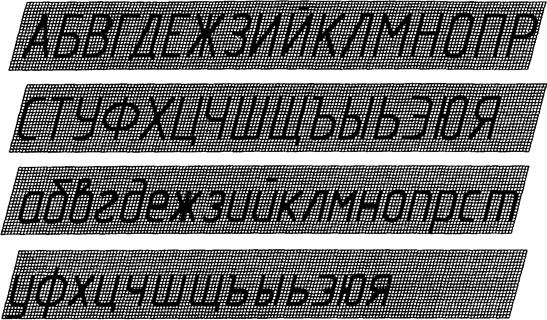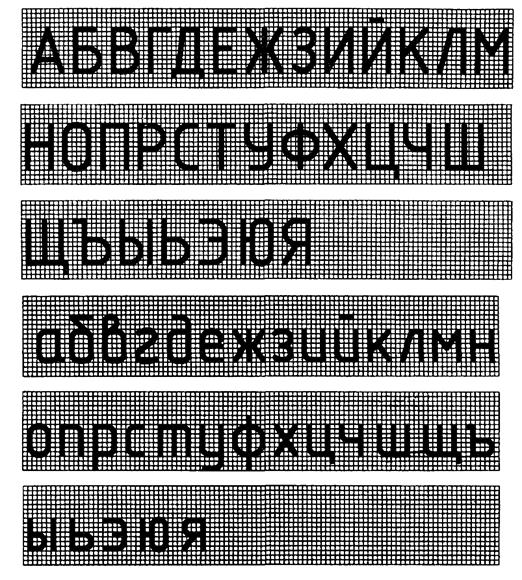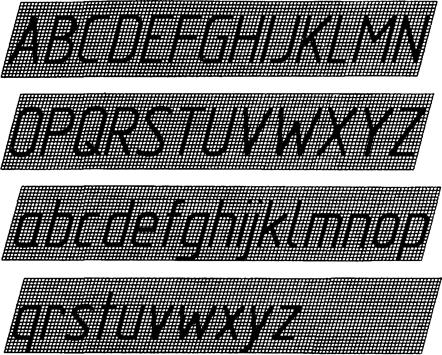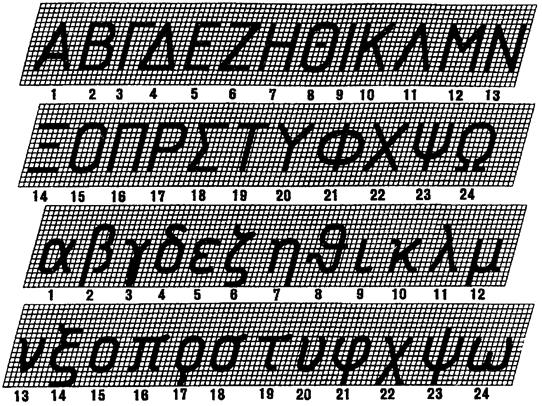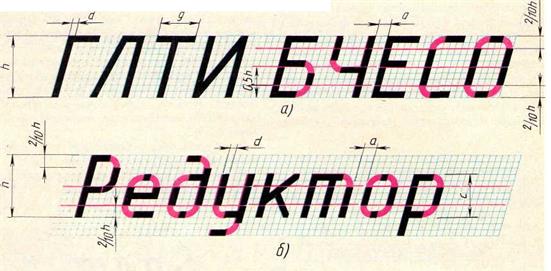
Шрифты чертежные
Линии.
При выполнении любого чертежа основными элементами являются линии. ГОСТ2.303—68 устанавливает начертания и основные назначения линий на чертежах всех отраслей промышленности и строительства.Наименование, начертание, толщина линий по отношению к толщине основной линии и основные назначения линий должны соответствовать указанным в табл. 1.
Таблица 1
Наименование Начертание Толщина линии по отношению к толщине основной линии Основное назначение
1.Сплошная толстая основная s Линии видимого контура Линии перехода видимые Линии контура сечения (вынесенного и входящего в состав разреза)
2.Сплошная тонкая От до Линии контура наложенного сечения Линии размерные и выносные Линии штриховки Линии-выноски Полки линий-выносок и подчеркивание надписей Линии для изображения пограничных деталей («обстановка») Линии ограничения выносных элементов на видах, разрезах и сечениях Линии перехода воображаемые Следы плоскостей, линии построения характерных точек при специальных построениях
3.Сплошная волнистая   Линии обрыва Линии разграничения вида и разреза
4.Штриховая   Линии невидимого контура Линии перехода невидимые
5.Штрихпунктир-ная тонкая От до Линии осевые и центровые Линии сечений, являющиеся осями симметрии для наложенных или вынесенных сечений
6.Штрихпунктир-ная утолщенная От до Линии, обозначающие поверхности, подлежащие термообработке или покрытию Линии для изображения элементов, расположенных перед секущей плоскостью («наложенная проекция»)
7.Разомкнутая От s до Линии сечений
8.Сплошная тонкая с изломами От до Длинные линии обрыва
9.Штрихпунктир-ная с двумя точками тонкая От до Линии сгиба на развертках. Линии для изображения частей изделий в крайних или промежуточных положениях Линии для изображения развертки, совмещенной с видом
Толщина сплошной основной линии s должна быть в пределах от 0,5 до 1,4 мм в зависимости от величины и сложности изображения, а также от формата чертежа. Толщина линий одного и того же типа должна быть одинакова для всех изображений на данном чертеже, вычерчиваемых в одинаковом масштабе. Длину штрихов в штриховых и штрихпунктирных линиях следует выбирать в зависимости от величины изображения. Для штриховой линии длина штрихов равна примерно от 2 до 8 мм (для формата А3 – 5мм), рассто­яние между штрихами 1...2 мм. Для штрихпунктирной линии длина штрихов должна быть равна примерно от 5 до 30 мм (для формата А3 – 15мм), расстояние между штрихами рекомендуется брать 2...3 мм. Штрихи в линии и промежутки между штрихами в линии должны быть приблизительно одинаковой длины. Штрихпунктирные линии должны пересекаться и заканчиваться штрихами.
Штрихпунктирные линии, применяемые в качестве центровых, следует заменять сплошными тонкими линиями, если диаметр окружности или размеры других геометрических фигур в изображении менее 12 мм (рис. 1.3).
Рис. 1.3
Длина штрихов разомкнутой линииберется 8...20 мм в зависимости от величины изображения (для формата А3 – 10мм). Для сложных разрезов и сечений допускается концы разомкнутой линии соединить штрихпунктирной тонкой линией.
Примеры применения линий показаны на рис. 1.4. Номера позиций соответствуют номерам пунктов табл. 1.
Рис. 1.4
Чертежи и прочие конструкторские документы всех отраслей промышленности и строительства содержат необходимые надписи: название изделий, размеры, данные о материале, обработке деталей, специфика­ции и другие надписи.Если надписи на чертежах сделаны небрежно, то при изготовлении деталей по таким чертежам возможны ошибки.ГОСТ 2.304—81 (устанавливает чертежные шрифты, наносимые на чертежи и другие технические документы всех отраслей промышленности и строительства.
Размер шрифта h - величина, определенная высотой прописных букв в миллиметрах.
Высота прописных букв h измеряется перпендикулярно к основанию строки.
Высота строчных букв с определяется из отношения их высоты (без отростков k) к размеру шрифта h, например, с = 7/10 h (рис. 1.5 и 1.6).
Ширина буквы g - ширина буквы определяется по отношению к размеру шрифта h, например, g = 6/10 h, или по отношению к толщине линии шрифта d, например, g = 6 d.
Толщина линии шрифта d - толщина, определяемая в зависимости от типа и высоты шрифта.
Рис. 1.5 Рис. 1.6
Вспомогательная сетка - сетка, образованная вспомогательными линиями, в которые вписываются буквы. Шаг вспомогательных линий сетки определяется в зависимости от толщины линий шрифта d (рис. 1.7).
Рис. 1.7
Устанавливаются следующие типы шрифта:
тип А без наклона (d = 1/14 h) с параметрами, приведенными в табл. 2;
тип А с наклоном около 75° (d = 1/14 h) с параметрами, приведенными в табл. 2;
тип Б без наклона (d = 1/10 h) с параметрами, приведенными в табл. 3;
тип Б с наклоном около 75° (d = 1/10 h) с параметрами, приведенными в табл. 3.
Таблица 2
Шрифт типа А (d = h /14)
Параметры шрифта Обозначение Относительный размер Размеры, мм
Размер шрифта -
высота прописных букв h (14/14) h l4d 2,5 3,5 5,0 7,0 10,0 14,0 20,0
высота строчных букв с (10/14) h 10 d 1,8 2,5 3,5 5,0 7,0 10,0 14,0
Расстояние между буквами а (2/14) h 2 d 0,35 0,5 0,7 1,0 1,4 2,0 2,8
Минимальный шаг строк (высота вспомогательной сетки) b (22/14) h 22 d 4,0 5,5 8,0 11,0 16,0 22,0 31,0
Минимальное расстояние между словами е (6/14) h 6 d 1,1 1,5 2,1 3,0 4,2 6,0 8,4
Толщина линий шрифта d (1/14) h d 0,18 0,25 0,35 0,5 0,7 1,0 1,4
Таблица 3
Шрифт типа Б (d= h /10)
Параметры шрифта Обозначение Относительный размер Размеры, мм
Размер шрифта -
высота прописных букв h (10/10) h 10 d 1,8 2,5 3,5 5,0 7,0 10,0 14,0 20,0
высота строчных букв с (7/10) h 7 d 1,3 1,8 2,5 3,5 5,0 7,0 10,0 14,0
Расстояние между буквами а (2/10) h 2 d 0,35 0,5 0,7 1,0 1,4 2,0 2,8 4,0
Минимальный шаг строк (высота вспомогательной сетки) b (17/10) h 17 d 3,1 4,3 6,0 8,5 12,0 17,0 24,0 34,0
Минимальное расстояние между словами е (6/10) h 6 d 1,1 1,5 2,1 3,0 4,2 6,0 8,4 12,0
Толщина линий шрифта d (1/10) h d 0,18 0,25 0,35 0,5 0,7 1,0 1,4 2,0
ГОСТ 2.304—81 устанавливает следующие размеры шрифта: (1,8); 2,5; 3,5; 5; 7; 10; 14; 20; 28; 40. Примене­ние шрифта 1,8 не рекомендуется и допускается только для типа Б. Построение шрифта во вспомогательной сетке показано на рис. 1.8.
Рис. 1.8
Начертание букв русского алфави­та показано на рис. 1.9 – 1.12
Шрифт типа А с наклоном
Рис. 1.9
Шрифт типа А без наклона
Рис. 1.10
Шрифт типа Б с наклоном
Рис. 1.11
Шрифт типа Б без наклона
Рис. 1.12
Начертание букв латинского и греческого алфавитов шрифтом типа Б с наклоном 75° показано на рис. 1.13 и 1.14. На рис. 1.15 показано написание арабских и римских цифр шрифтом типа Б с наклоном и без наклона.
Рис. 1.13
Рис. 1.14
Рис. 1.15
Начертание знаков шрифтом типа Б с наклоном приведено на рис. 1.16
Рис. 1.16
Для надписей чертежным шрифтом выполняется вспомогательная сетка сплошными тонкими линиями. При этом необходимо учесть разную ширину букв (рис. 1.17; буквы Ш, X, Ю). Расстояние между некоторыми буквами, например, Г и А (и в аналогичных сочетаниях букв) уменьшается до размера, равного толщине линии букв (рис. 1.18; буквы Г и Л). Прописные буквы по начертанию условно делят на три группы. При написании букв первой группы, например, Ш, Ц, Г, И нетребуются вспомога­тельные линии (рис. 1.17; буквы Ш, Ц, X). Для написа­ния второй группы посередине сетки проводят линию, над которой или под которой располагаются средние элементы букв, например букв Э, Ч, Ю, Б (рис. 1.17, 1.18). Для написания букв третьей группы - две линии, которые на­ходятся на расстоянии 3/14 h (для шрифта типа А) от верхней и нижней линии, ограничивающие скругление букв (рис. 1.17; буквы Э, Ю). В шрифте типа Б эти две линии расположены на расстоянии 2/10 h (рис. 1.18, а). Это нужно учитывать и при выполнении строчных букв (рис. 1.18, б).
ШРИФТ ТИПА А
Рис. 1.17
ШРИФТ ТИПА Б
Рис. 1.18
Для написания шрифтов малого размера применяют упрощенную сетку. На рис. 1.19 показано вписывание букв шрифта типа Б в обычную (рис. 1.19, а) и упрощенную сетку (рис. 1.19, б).
При выполнении надписей стандартным шрифтом типа Б размером 10(h) проводят все вспомогательные горизонтальные прямые линии, определяющие границы строчек шрифта. Проводят две горизонтальные линии на расстоянии 10 мм (высот шрифта h), на полученной строке откладывают отрезки, равные ширине букв плюс расстояние между буквами. Например, для буквы А этот отрезок равен 9/10/г (7/10/h — ширина буквы, 2/10/h — расстояние между буквами). При разметке строки учитывают сочетания букв типа РА, ГА, ТА и т. п. Наклонные линии для сетки под углом 75° проводят через намеченные точки при помощи двух треугольников: с углом 45° и с углами 30 и 60° (рис. 1.20).
Рис. 1.19
Рис. 1.20